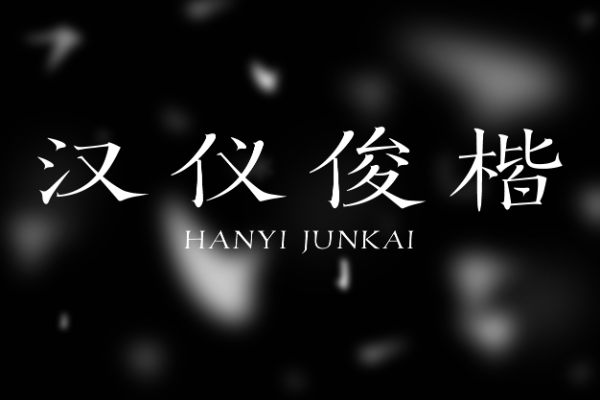
汉仪俊楷 W
这款字体笔画内部有明显粗细对比,起笔收笔有细有粗相互照应。笔画纤细处尖锐浏亮,衬托出通透的字形白空间,带来清新恬淡的感觉。转折、顿笔处被加粗、放大处理,与纤锐的笔画形成对比,带来俊秀的感觉。字形结构扁宽,笔画外张,最右侧竖笔画向内弯曲,使得结构在端稳中多了一丝动感,传递出闲适的感觉。整体风格清秀雅逸,适合排布一些较短的文案,用在茶点、文具、首饰等于传统文化有关的场合,以渲染怡情养性、气定神闲的氛围。